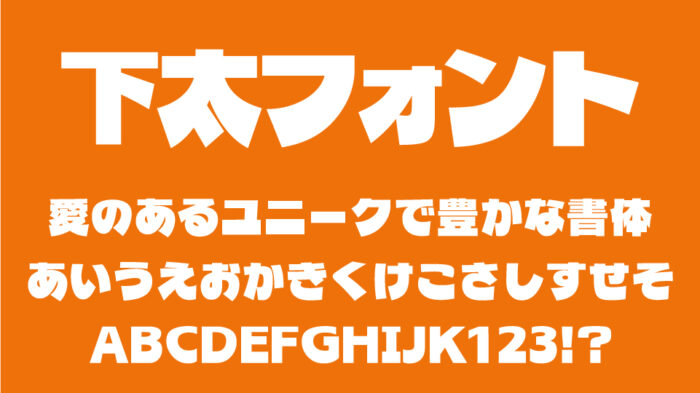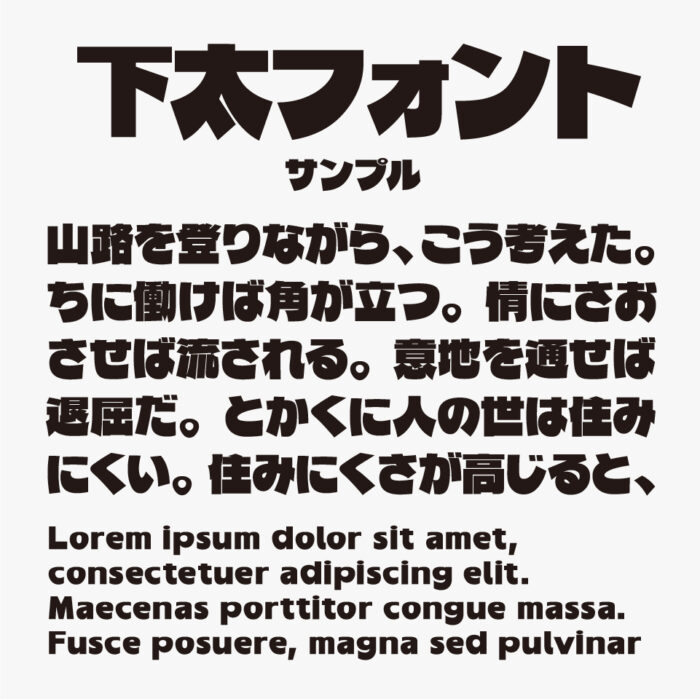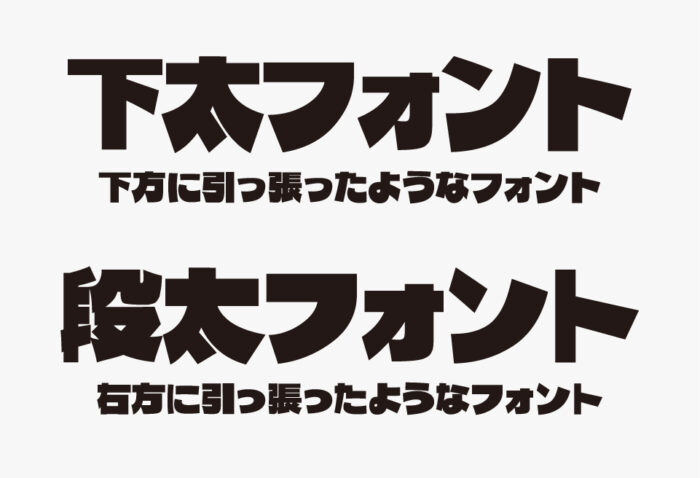
下太フォント
下太フォントは、「源暎きわみゴ」フォントをベースに下方へ引っ張ったような重力感のあるユニークなデザインフォントです。
上部をコンパクトに抑え、下部を大きく太らせた遊びごころのあるユニーなデザインにより、太いウエイトと特徴的なシルエットで、見た瞬間に視線を引きつけるパワーがあるフォントとなっています。
コミカルな雰囲気もあるので、動画テロップやサムネイルなどにもぴったりです。
下太フォントは下方に引っ張ったようなデザインですが、同じく右方に引っ張った「段太フォント」もユニークなので、両方揃えておくと場面にあわせて使い分けができそうです。